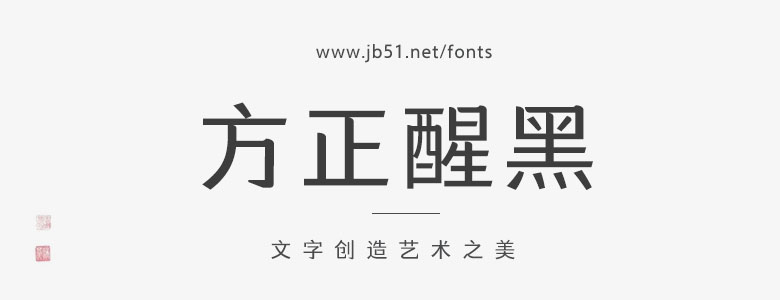
醒黑這款字屬于黑體家族,區(qū)別于傳統(tǒng)黑體直角硬朗的風(fēng)格,部分筆畫的起筆改為斜圓,讓原本封閉的結(jié)構(gòu)斷開,增加了柔和感。點畫和勾畫的不等粗處理及橫畫收筆的斜切,又增加了趣味感。拐角處增加的飾線與橫豎風(fēng)格呼應(yīng),形成了統(tǒng)一。這款字體共6個系列,適合多種媒介平臺的標(biāo)題和正文使用。